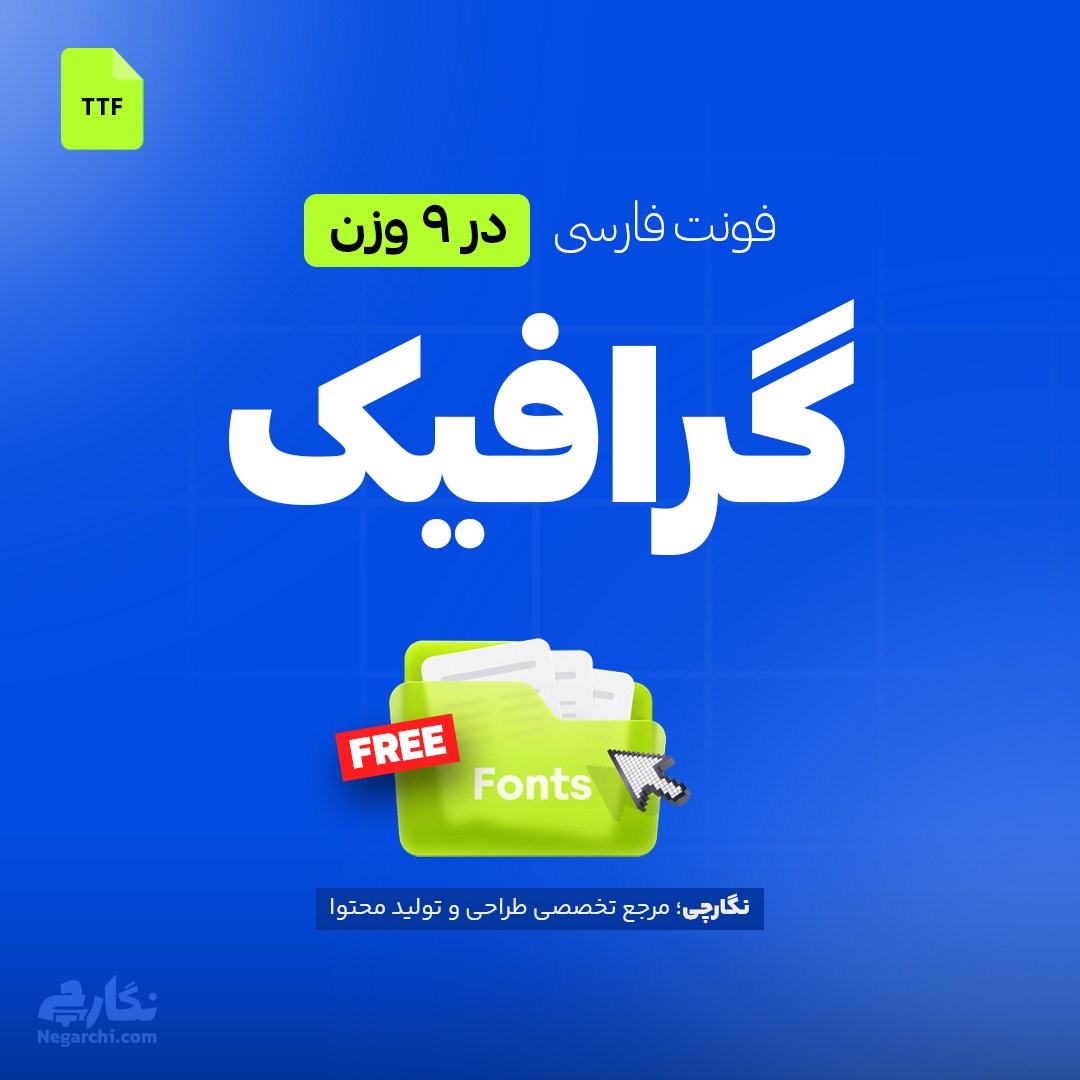
فونت فارسی گرافیک Graphik یک تایپفیس دوستانه و فانتزی با ۹ وزن مختلف است که برای طراحی پست و محتوای اینستاگرام، تامنیل یوتیوب، پوستر، لوگوتایپ، بستهبندی و استفاده در نرمافزارهای موبایل و دسکتاپ کاربرد دارد.
فونت فارسی گرافیک یک فونت با حس دوستانه و فانتزی است که بهخصوص در شبکههای اجتماعی مانند اینستاگرام و یوتیوب طرفداران زیادی دارد. این تایپفیس در ۹ وزن مختلف، از نازک تا سوپر بولد، ارائه میشود و به همین دلیل میتوان از آن برای تیتر، متن و بخشهای مختلف طراحی استفاده کرد.
مجموعه فونت گرافیک علاوه بر قابلیت تایپ فارسی، امکان تایپ انگلیسی را نیز فراهم میکند و میتوانید متنهای انگلیسی را در همان وزنهای فارسی بنویسید. تنوع وزنها باعث میشود فونت گرافیک برای طراحیهایی با نیاز به ضخامتهای متفاوت، انتخاب کاربردی باشد.
فونت گرافیک برای افرادی مناسب است که در زمینه طراحی و تولید محتوای دیجیتال فعالیت میکنند و به دنبال یک فونت فارسی متفاوت با ظاهر دوستانه و فانتزی هستند. از این فونت میتوانید در موارد زیر استفاده کنید:
وجود ۹ وزن مختلف در فونت گرافیک امکان ایجاد تنوع در طراحی را فراهم میکند. وزنهای ضخیمتر برای تیترها، تامنیلها و نوشتههای تبلیغاتی و وزنهای سبکتر برای متن و بخشهای ظریفتر طراحی قابل استفاده هستند. قابلیت تایپ فارسی و انگلیسی نیز باعث میشود بتوان از این فونت در پروژههایی با محتوای دو زبانه استفاده کرد.
فونت گرافیک در ۹ وزن مختلف ارائه میشود و این تنوع وزن یکی از ویژگیهای اصلی آن است. گستره وزنها از حالتهای نازک تا وزنهای بسیار ضخیم و سوپر بولد را شامل میشود و به طراح اجازه میدهد متناسب با نوع پروژه، ضخامت مناسب را انتخاب کند. به همین دلیل میتوان از فونت گرافیک هم برای تیترهای برجسته و تبلیغاتی و هم برای متنها و بخشهای ظریفتر طراحی استفاده کرد.
بله، فونت گرافیک به دلیل ظاهر دوستانه و فانتزی و همچنین تنوع ۹ وزن، برای تولید محتوای شبکههای اجتماعی گزینه مناسبی است. از این فونت میتوان در طراحی قالب پست اینستاگرام، نوشتههای تبلیغاتی، تامنیلهای یوتیوب و سایر محتوای تصویری استفاده کرد. وزنهای ضخیمتر برای نوشتههایی که باید در نگاه اول دیده شوند کاربرد دارند و وزنهای سبکتر نیز برای متنها و جزئیات طراحی قابل استفاده هستند.
فونت گرافیک علاوه بر تایپ فارسی، امکان تایپ انگلیسی را نیز دارد و میتوان متن انگلیسی را در همان وزنهای مختلف فونت استفاده کرد. این قابلیت برای طراحیهایی که شامل ترکیب نوشتههای فارسی و انگلیسی هستند کاربردی است. بنابراین میتوان از گرافیک در پروژههایی مانند پستهای شبکههای اجتماعی، پوستر، تبلیغات، طراحی سایت، بستهبندی و تامنیلهایی که محتوای دو زبانه دارند استفاده کرد.